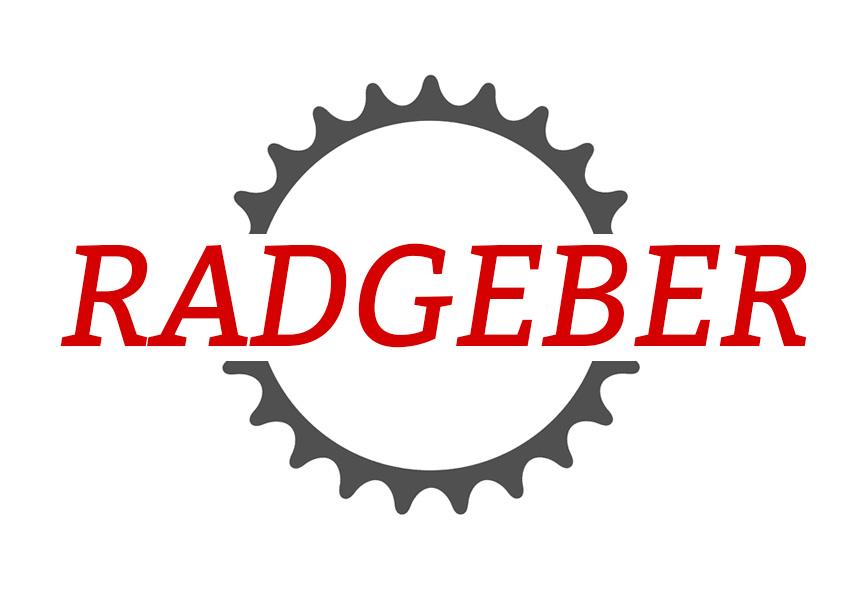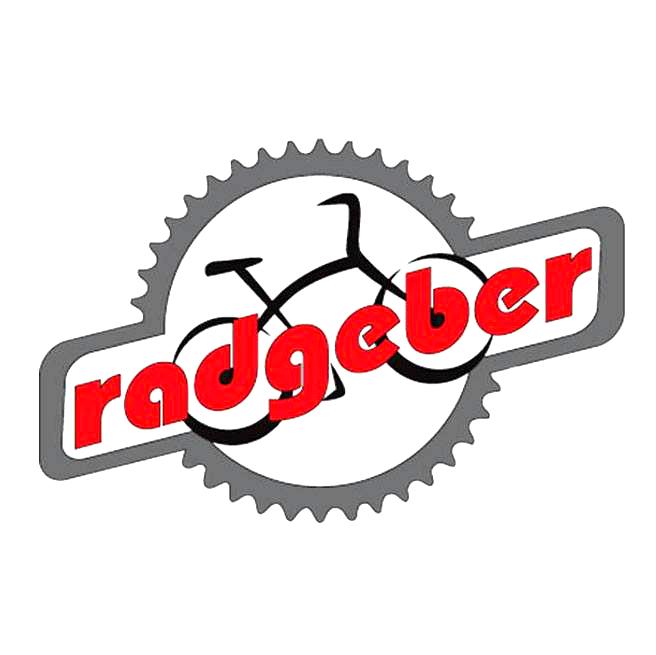
(freie) Schrift für Fahrradladen gesucht (Logo redesign)
ich versuche mich gerade an einem Redesign von unserem Logo. Das aktuelle seht ihr unten links. Die Idee mit dem Kettenblatt als Hintergrund finde ich nett und es ist auch ein gängiges Motiv in Logos von Fahrradläden. Das Fahrrad in der Mitte und den Schriftzug finde ich aber eher unpassend - besonders die Schriftart (ITC Bauhaus ?). Sie ist mir zu geometrisch und strahlt, wie ich finde, einen Technizismus aus, der zu uns nicht so richtig passt. Der Versuch mit dem aufstrebenden Winkel eine Dynamik zu transportieren wirkt etwas verkrampft (genauso wie die Achsen im "d" und "b") und widerspricht auch meiner Meinung nach der statischen geometrischen Schrift (die ich ja sowieso loswerden will). Das rot sollte aus Gründen der Wiedererkennung bleiben, auch wenn es mir eigentlich zu grell und aggressiv ist - ich habe es im Entwurf etwas abgedunkelt.
Findet ihr meine Analyse soweit nachvollziehbar?
Der erste grobe Entwurf ist unten rechts. Ich hab hier im Freefonts-Thread ein bisschen gestöbert und bin auf die Bitter gestoßen, die ich in kursiv erst mal ganz passend fand. Was sagt ihr dazu?
Wie ich schon angedeutet habe sind wir ein kleines Fahrradgeschäft / Werkstatt mit drei Mitarbeitern. Unsere Kundschaft besteht z.Zt. hauptsächlich aus Pendlern, Freizeitfahrern und (noch) wenigen Radsportlern aus dem näheren Umkreis einer ländlichen, aber wachsenden suburbanen Umgebung. Wir verkaufen alle arten von Rädern, aber hauptsächlich Mountainbikes, Trekkingräder und natürlich E-Bikes.
Die Schrift sollte also sein:
warm und freundlich, aber nicht verspielt, bodenständig aber nicht konservativ, präzise und verlässlich, aber nicht technizistisch, dynamisch, aber nicht zu sportlich, handwerklich, aber nicht zu grob, minimalistisch, aber nicht zu clean.
Ich freue mich auf offene Kritik, Alternativen oder Gegenvorschläge!
nach meinem persönlichem Geschmack finde ich weder Italic noch Serifen als angemessen. Ich würde da einen sehr viel schlichteren Ansatz ins Auge fassen. Eine relativ neutrale Serifenlose aufrecht wäre meine Vorgehensweise. Ein praktischer Nebeneffekt wäre die Möglichkeit die Schrift aus dem Logo auch auf anderen Dokumenten, vom Brief bis zum Plakat, verwenden zu können.
Daher mein Vorschlag: Die Nimbus Sans L öder ähnliches aufrecht, ggf. die Condensed und/oder Bold, dann diese Schrift auch für den restlichen Grafikkram verwenden.
In die Richtung gehen da noch einige andere Schriften, wie die Roboto 2014
und die Cooper Hewitt, auch wenn es diese nur in einer Laufweite gibt:
Einfach mal versuchen den Ansatz nachzuvollziehen. Unspektakulär, aber effizient ...
Irgendwie scheint mir Dein Schriftzug unausgewogen. Gegen die Schrift selbst ist nichts einzuwenden, aber für mein Auge bedürfte es im Versalsatz noch der Zurichtung. Das ist aber etwas für einen Profi.
danke für die Ideen! Vor allem an den Aspekt der universellen Verwendbarkeit habe ich nicht gedacht - bzw. hätte dafür noch eine weitere Schrift gesucht. Im Moment wird in Rechnungen usw. teilw. Comic Sans genutzt - ich glaub das spricht für sich.
Die TexGyre Heros bzw. Nimbus Sans L finde ich richtig gut. Im Logo würden mir aber das "R" und das "G" nicht so gut gefallen. Das liegt auch sicher an den Verwendung im Versalsatz wofür die vielleicht nicht vorgesehen ist.
Die Cooper Hewitt Book oder Roboto 2014 in schmal evtl. fett würden mir im Logo am besten gefallen - die Roboto macht sich auch im Fließtext nicht schlecht, wie ich finde - bei der Cooper Hewitt finde ich die Oberlänge etwas zu groß, dafür gefallen mir die etwas eckigeren Kurven bei den Majuskeln - wirkt dann schön plakativ.
Ich werde mit den dreien wahrscheinlich erst mal weitermachen und melde mich nochmal sobald ich was zeigen kann.
Ich merke gerade, dass der Versalsatz generell nicht ganz so einfach ist. Das Logo ist aber auch nur ein Grobentwurf . Ich wollte erst mal vermeiden mich sofort auf etwas einzuschießen um dann auf dem falschen Dampfer zu sein.
Ich finde den Entwurf gut und die Slab Serif auch passend. Nimbus/Helvetica ist alles andere als dynamisch – da würde ich absolut von abraten.